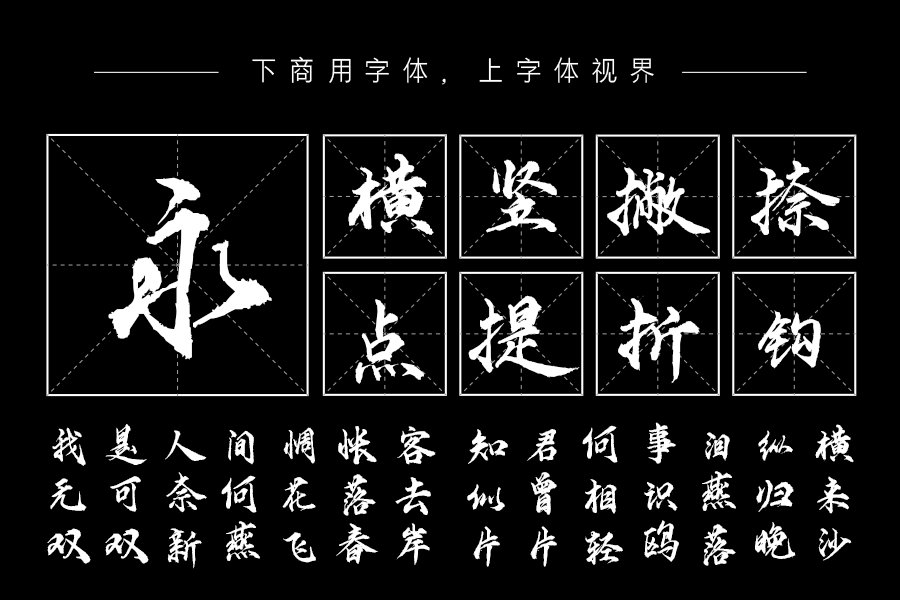
​电影海报中的书法字体
电影海报设计中最常见的是书法字体,因为书法字体比较能充分代表中国传统文化,并以其特有的韵律、节奏体现美感。
由字体视界对外公开首发,供个人免费商用的云江体也是一款可以用于影视场景中使用的字体。该字体笔势婉转灵动且流畅自然,具有独特的韵味,又有独特的文化魅力及笔意境界。笔画细致流畅,结构紧凑,笔意拙中带巧,不避锋芒。
云江体
汉呈王天喜榜书字体是典型的行楷字体风格,看上去非常的端正秀美,充满了古典气息。该字体曾于影视剧中用作片名。
汉呈王天喜榜书字体